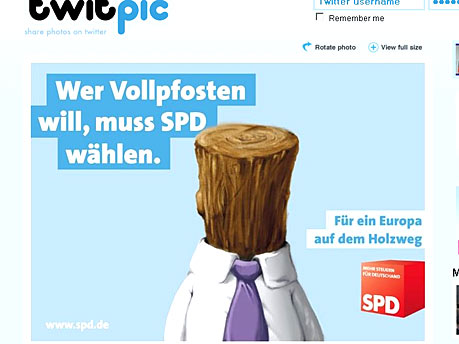
Ja was soll man sagen … – da ist der Shabby Chic wohl inzwischen sogar bis zur SPD vorgedrungen. Almost a trendsetter. ;-)
Das chic kannst Du streichen. Schäbig reicht schon vollkommen aus ... :baeh:
Seit vielen Jahren (seit der Agenda 2010?) gibt es nach meinen Wahrnehmungen besonders viele grafisch qualitativ hochwertige Parodien auf SPD-Plakate. Das geht dann rein biss in sauber gestaltete Grafiken und Typografie. Andere Parteien kamen/kommen da deutlich besser weg und die Parodien sind eher minderwertig. Noch sehr gut in der Erinnerung: 2009 versuchte es die SPD mit vergleichender Werbung und bekam dann eine Retourkutsche in Form einer Kunstaktion.
Hier findet man Hinweise auf die Kunstaktion:
Ja, Agenda 2010 und dessen Bestandteil Hartz-IV waren diesen Angaben nach der Auslöser für diesen kreativen Protest. Hatte die SPD damals wirklich die TheSans? Ja, doch ... Da hat sich jemand wirklich sehr viel Mühe gegeben. Auch die Grafiken entsprechen sehr genau dem Duktus der Vorlagen.
Als ich meinen ersten PC hatte, besaß ich dazu einen 14"-Monitor mit VGA-Auflösung (640 x 480 Pixel) und max 256 Farben - auf die ich schon fix Stolz war, saß ich im Büro vor einem EGA-Monitor.
Dazu ein 386SX mit 640MB RAM und einer "riesengroßen" 52MB Festplatte von Quantum. Aber darauf hatte ich dann CorelDRAW! 1.2, AutoCAD, Picture Publisher, WordStar für Windows, Windows3.1 natürlich, und irgendwie lief das eigentlich gar nicht so lahm, wie es im Vergleich zu den Daten heutiger Hardware hätte laufen müssen.
War vielleicht früher sauberer programmiert. Mein erster PC war ein Atari Mega ST 2. Ich habe da zwar nur Textverarbeitung (Signum) mit gemacht und ein wenig Pascal programmiert, aber eigentlich deutet schon die geringe Dateigröße von Signum darauf hin, dass Programme heutzutage eine Menge Ballast mit sich herumschleppen, oder? Ich bin mir nicht sicher. Signum passte jedenfalls auf wenige Disketten. Und der Monitor war monochrom. Dafür war die mechanische Tastatur der Hammer. Ich verstehe übrigens nicht, weshalb sich viele Leute fette Rechner kaufen, aber an der Tastatur sparen. Die Atari-Tastatur war jedenfalls besser als meine aktuelle Cherry-Tastatur (die ebenfalls mechanisch ist).